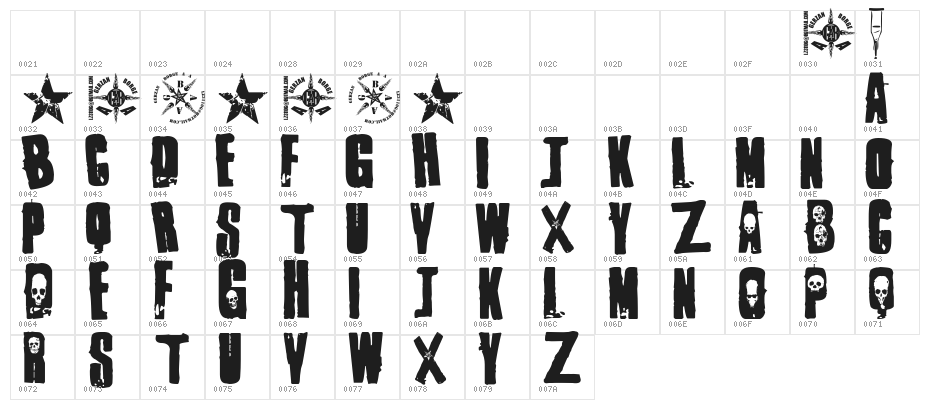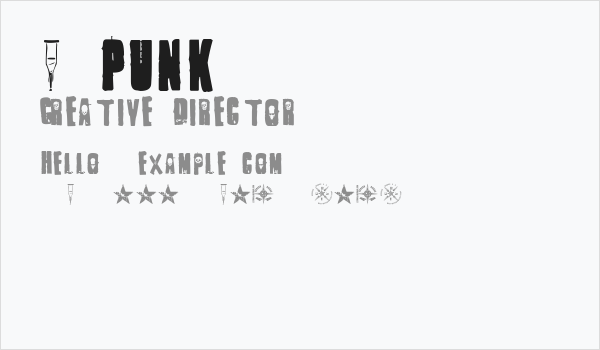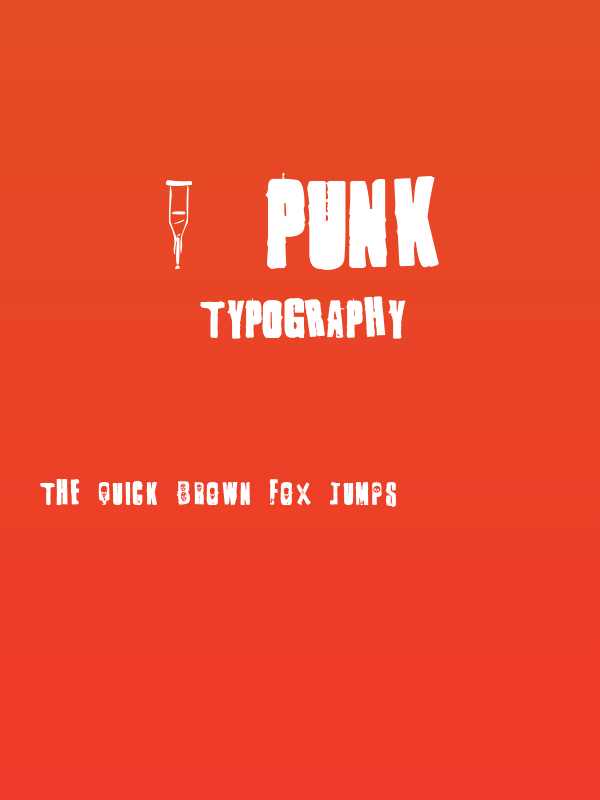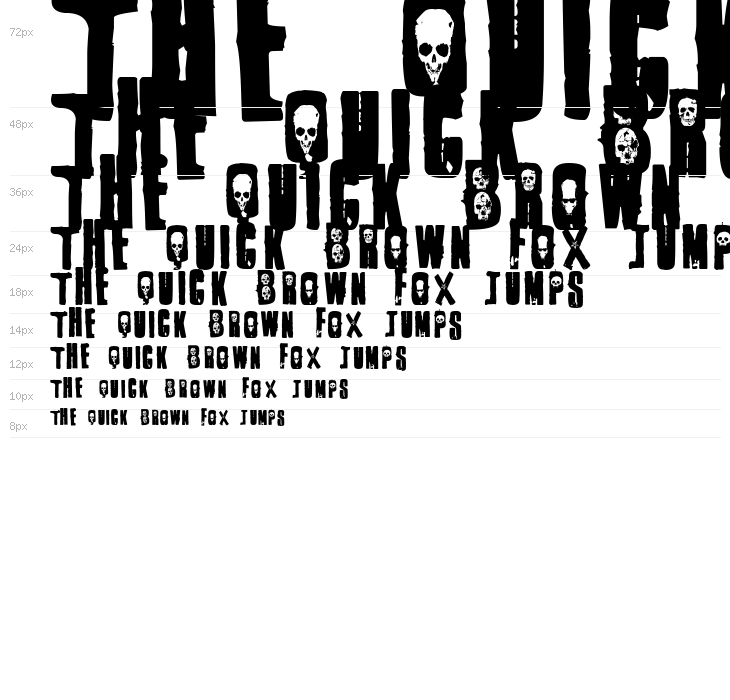
1 Punk Font
| Gesamtstil | Punk, Grunge, Edgy |
| Anwendungsfall | Logos, Posters, Album Covers |
| Vorgeschlagene Projekte | Ideal for music album covers, band posters, edgy fashion branding, and rebellious-themed designs. |